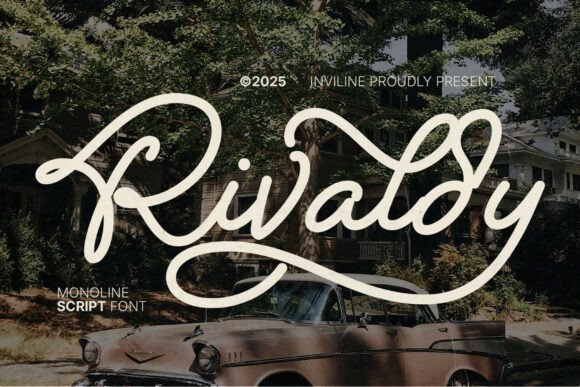
Rivaldy Monoline Script Pro
Rivaldy Monoline Script Proのような高品質の素材をお探しの場合、このプレミアムパッケージはクリエイティブなプロジェクトに素晴らしい選択です。
POD(オンデマンド印刷)製品、結婚式の招待状、またはソーシャルメディアのグラフィックを作成している場合でも、Rivaldy Monoline Script Proは理想的です。